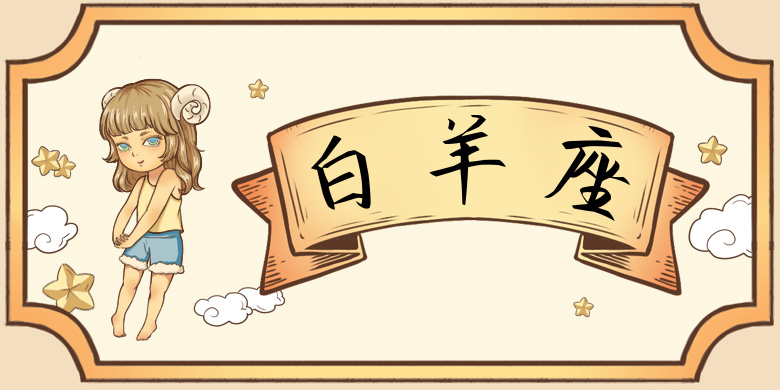
品牌:方正手迹设计师:余丹发行时间:2019字库编码:简繁扩展(GBK)分类:常规书写·硬笔字体属性:精品字
此款字笔画粗细变化有致,方正硬朗,字形笔触锋利,如剑浑厚力强。自然流畅,如行云流水。既体现了古意盎然之意,又具有中和圆融的独特面貌,字体阅读能感受到那股豪气。适用于文艺类的书刊、品牌广告和产品包装设计,以及社交网络的个性化用字。
品牌:方正手迹设计师:余丹发行时间:2019字库编码:简繁扩展(GBK)分类:常规书写·硬笔字体属性:精品字
此款字笔画粗细变化有致,方正硬朗,字形笔触锋利,如剑浑厚力强。自然流畅,如行云流水。既体现了古意盎然之意,又具有中和圆融的独特面貌,字体阅读能感受到那股豪气。适用于文艺类的书刊、品牌广告和产品包装设计,以及社交网络的个性化用字。